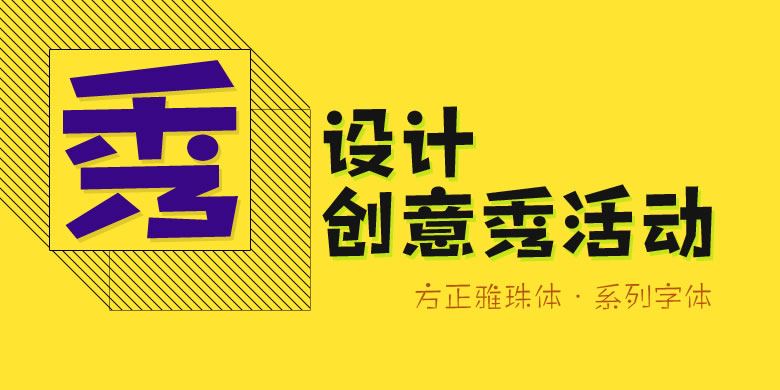
方正雅珠體繁體U方正雅珠体系列
品牌:方正字库设计师:郭炳权发行时间:2016字库编码:大陆简体(GB2312-80)、港台地区(BIG-5)、简繁扩展(GBK)分类:创意字体
方正雅珠体的字形结构和笔画造型是以图形化的手法设计的。这款字体的笔画以不规则的四边形构成,竖笔画呈梯形,部分点笔画处理成圆形,与四边形形成一种欢快的对比。字形上松下紧,重心下移,凸显稚气。方正雅珠体家族包含8种字重,个性天真可爱、单纯无邪,充满童趣,适用于儿童类品牌的广告和产品包装设计。